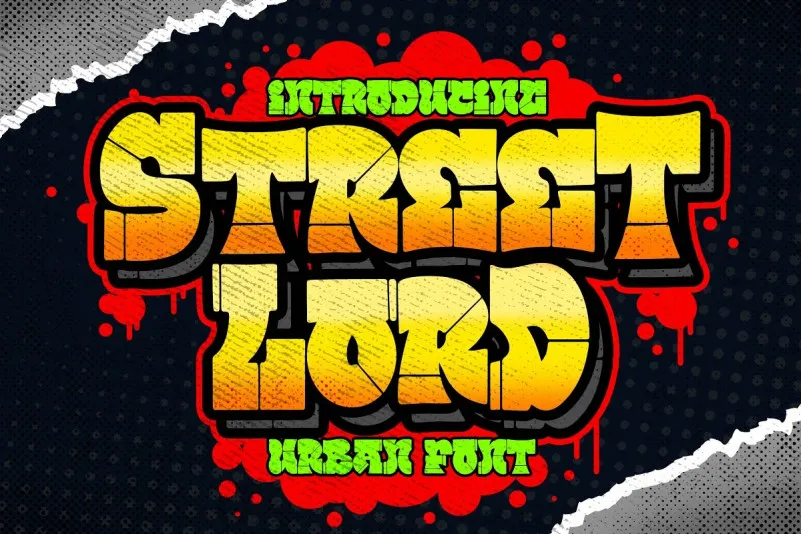
A Street Lord Font é uma fonte de tipo display inspirada na grafiteira com tons vibrantes e temática animada, perfeitamente adaptável para aplicações publicitárias. Criado pela Blankids Studio, esta fonte inclui um conjunto completo de linhas – outline e solid – que permitem aos designers ajustarem o tom dos caracteres para obter um resultado impecável. Com seu design único inspirado na grafitagem e tema divertido, a Street Lord é uma escolha ótima para aplicativos como posters de graffiti, música do hip-hop, cartazes infantis, livros infantis ou mesmo como fonte para mangás e quadrinhos infantis. Perfecta para criar designs visuais chamativas e vibrantes que capturam o espírito de grafitagem e cultura urbana. Experimente a Street Lord Font para seu próximo projeto criativo em tipos de display, garantindo uma experiência única e visualmente impactante.